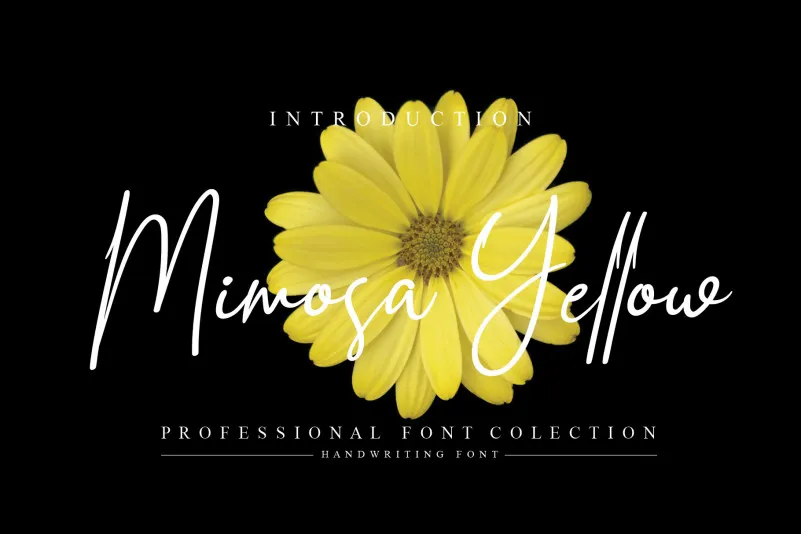
Mimosa Yellow Script Font – Fonte Grátis
Mimosa Yellow Script Font
A fonte Mimosa Yellow Script é uma sugestão para aqueles que buscam um toque autêntico e elegante no seu design. Desenvolvida por andikastudio, essa fonte de escrita feita à mão transmite tranquilidade e sofisticação. Seu estilo relaxado e antigo faz com que ela possa ser usada em diversos projetos, desde cartões personalizados até websites responsivos. Suas linhas delicadas e gestos naturais criam um design fluído, oferecendo aos designers uma opção perfeita para incluir em sua biblioteca de fontes. Composta por andikastudio, a Mimosa Yellow Script é ideal tanto para aqueles que buscam algo romântico e descontraído quanto para aqueles que valorizam o clássico na composição visual. Ela se destaca como uma escolha versátil para qualquer projeto de design.